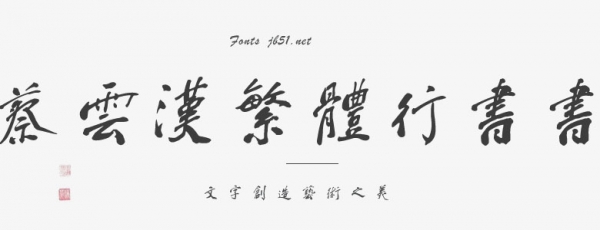
蔡云漢繁體行書書法字體是一款具有很接地氣的手寫中文字體,她比較適合用于相關(guān)的廣告設(shè)計,PS軟件內(nèi)嵌以及海報設(shè)計應(yīng)用等,字體家網(wǎng)站是一家專業(yè)發(fā)布字體下載和免費字體下載和正版授權(quán)的字體網(wǎng)站,有葉根友字體以及漢儀字體,方正字體等。